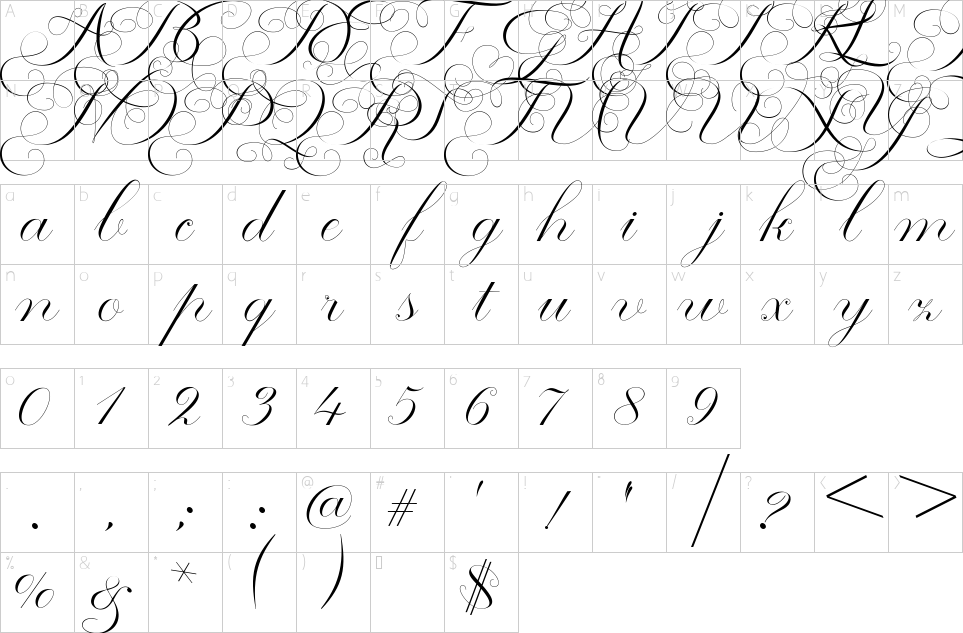
Descubra a elegância e a delicadeza da Manhattan Calligraphy font. Desenvolvida pela Shape Studio, essa fonte gráfica é perfeita para quem busca um estilo elegante e sofisticado em suas criações. Com uma aparência envolvente e natural, ela é uma escolha ideal para aqueles que desejam adicionar um toque especial aos seus projetos de design, seja em seu website, redes sociais ou em qualquer outro documento. Sua facilidade de uso e variedade de recursos a tornam uma opção sólida para designers de todos os níveis. Baixe Manhattan Calligraphy font gratuitamente e experimente a beleza desta fonte. Seu design é uma escolha segura para qualquer projeto que busque uma aparição sofisticada e elegante.